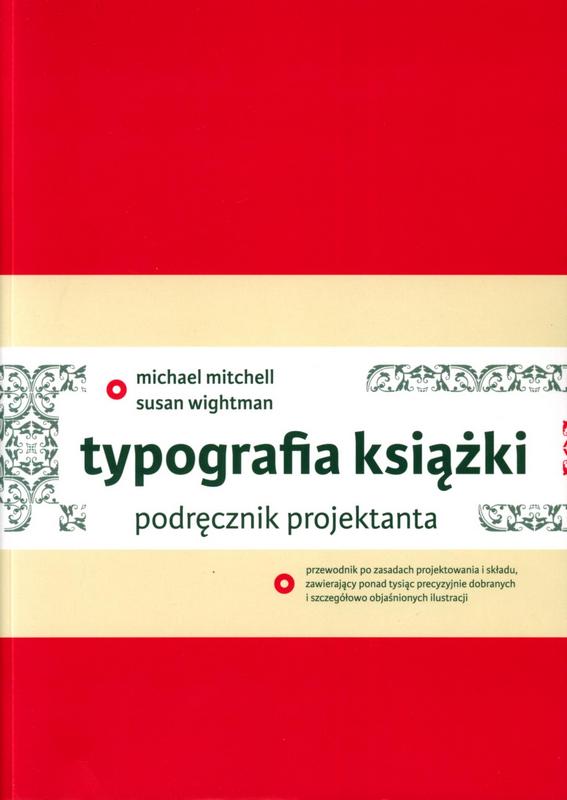
Typografia książki:
podręcznik projektanta
Michael Mitchell (1939-2017)
Susan Wightman
Typografia książki… to funkcjonalny i czytelny podręcznik. To doskonałe wprowadzenie do samodzielnego projektowania, a także źródło wiedzy o typografii i technikach druku. Ten bogaty zbiór obejmuje każdy istotny element procesu projektowania książki. Zamiast nudnych opisów z historii typografii, słownikowych definicji, czy też wyliczania nienaruszalnych reguł dostajemy konkretne przykłady zastosowania nowoczesnych fontów, dokładny opis ich wizualnego oddziaływania na czytelnika, zalecenia dotyczące właściwego doboru ich rozmiaru, tak aby spełniały wymogi czytelności oraz estetyki tekstu, jak również towarzyszących mu ilustracji. [od wydawcy]